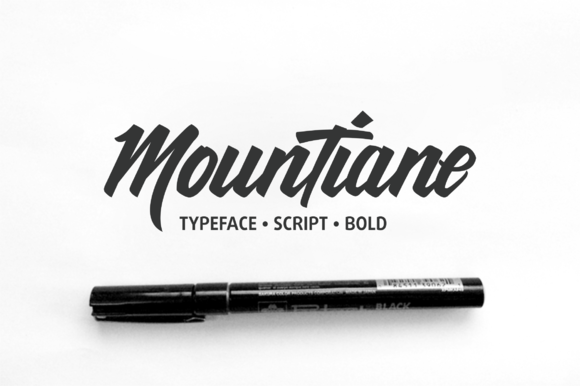
MounTiane Typeface – Fonte Grátis
MounTiane Typeface
A fonte MounTiane Typeface é uma criação inspirada na elegância e poder das escritas a mão, trazendo consigo características únicas que tornam-a perfeita para criar logotipos, tipografias de qualidade ou qualquer projeto gráfico em que um estilo elegante seja valorizado. Desenvolvida pelo designer 178-MC, essa fonte é uma excelente escolha para quem deseja transpor o encanto da escrita a mão no seu design digital. Com linhas suaves e traços finos, MounTiane captura o sentimento de elegância e controle que um designer pode encontrar ao escrever por conta própria em seus trabalhos. A versatilidade dessa fonte a torna uma escolha segura para qualquer projeto de tipo ou logotipo. Não perca essa oportunidade de explorar os limites do seu design digital, com MounTiane Typeface.